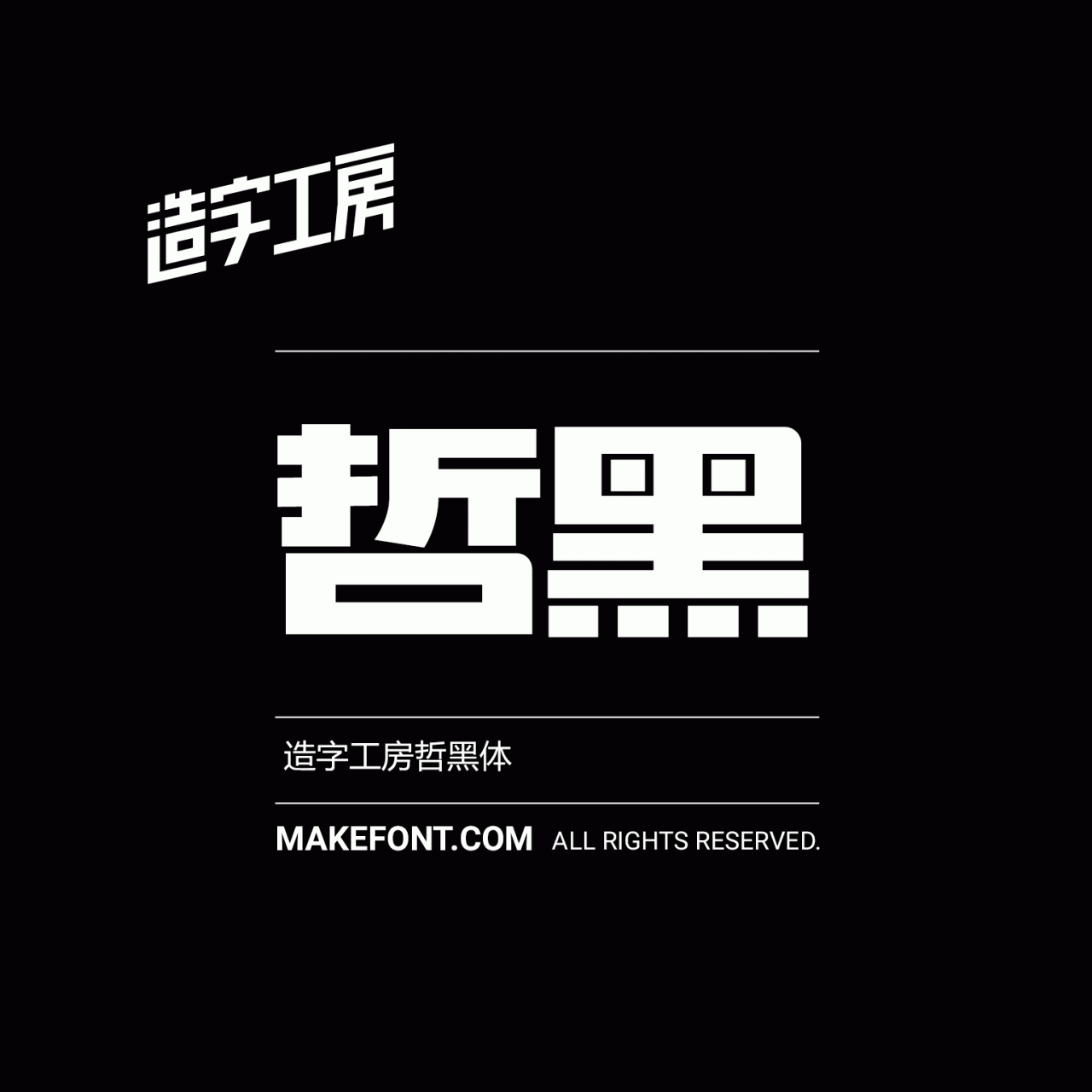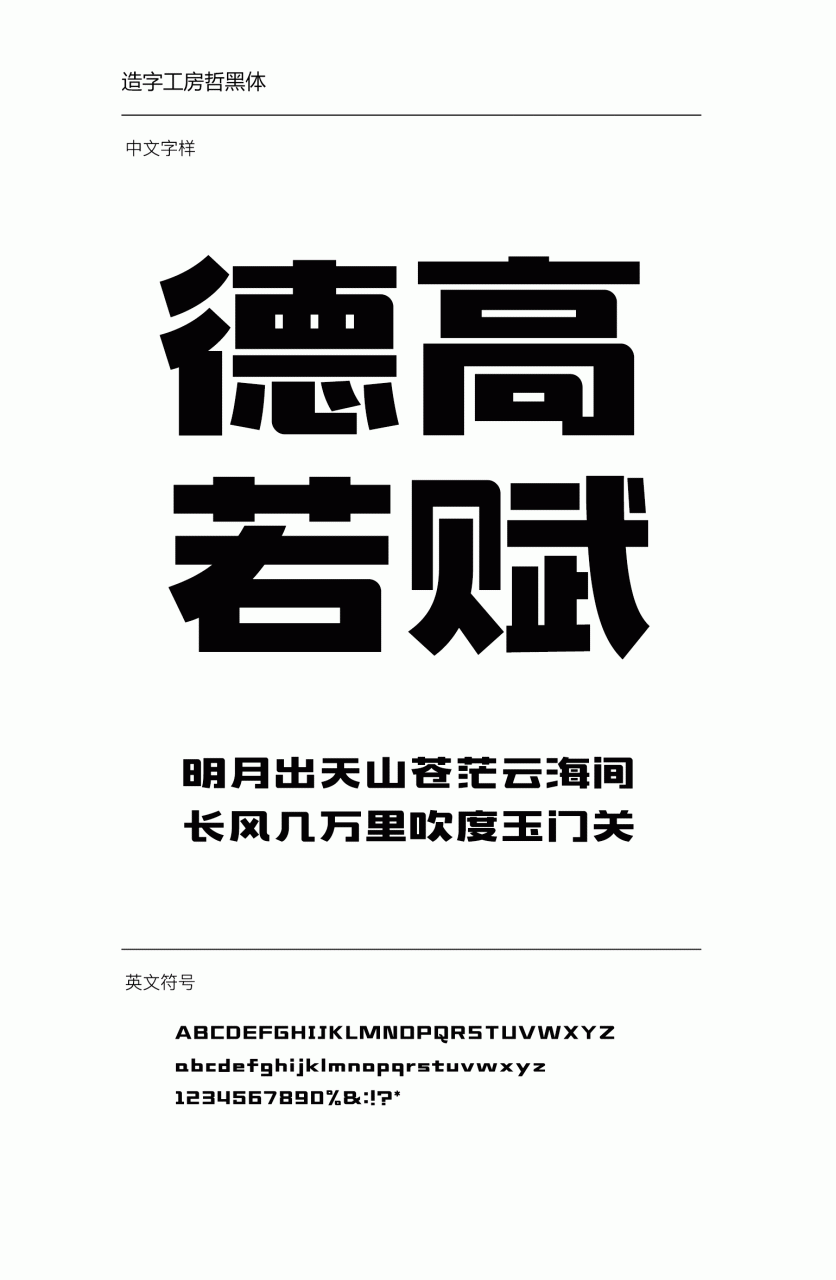
造字工房哲黑常规体设计说明
造字工房哲黑体结构明朗、字形端正、笔画横平竖直,字形整体风格刚劲有力,其笔画古朴沉厚又不失沉稳之风。适用于大标题及个性品牌设计推广等环境。本字体为简体字库,采用OpenType/CID格式,Adobe-GB1-5编码。基于中华人民共和国GB2312-80字符集标准,另按需添加101个汉字。共收容字数6864CJK汉字,ASCII常用字符100个。